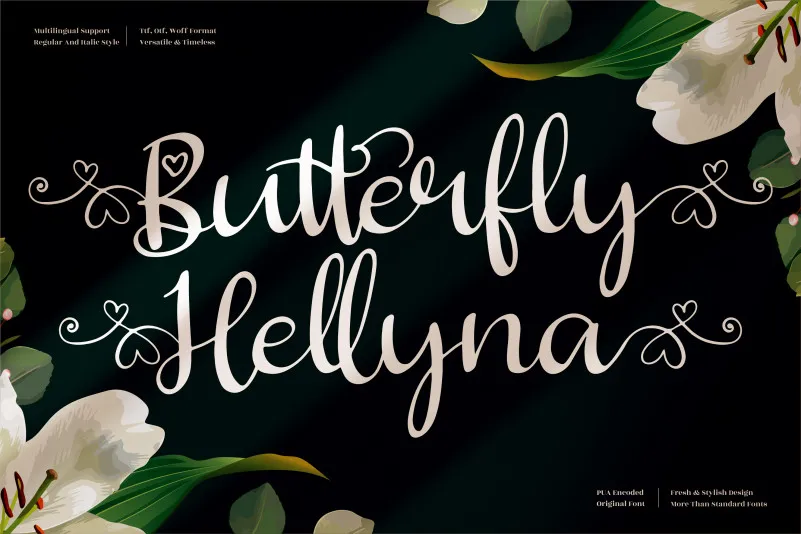
A Butterfly Hellyna Font é uma elegante fonte script que traz um toque delicado e detalhista aos seus projetos. Compondo perfeitamente a categoria de letras góticas, esta fonte é uma escolha inspirada para quem busca qualidade em cada linha e curva. Ela se destaca como uma excelente adição para qualquer coleção de fonts, especialmente quando aplicada em criações que valorizam elegância e sutileza. Seja em designs de arte ou até mesmo em editoriais gráficos, a Butterfly Hellyna Font terá um impacto significativo, potencializando a beleza do seu trabalho. Inspirado no designer perspectype, esta fonte é uma escolha inteligente para quem busca uma letra que não só se destaca, mas também complementa e enriquece sua produção visual.